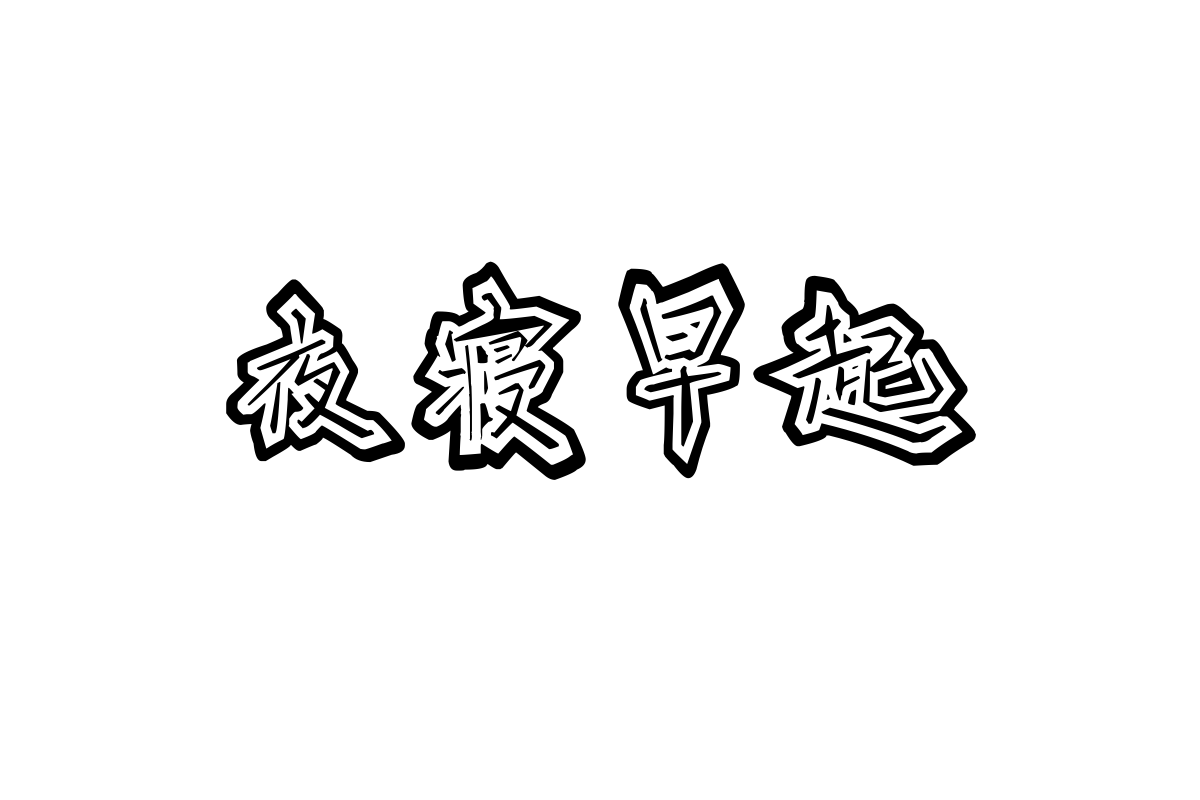
汉仪新蒂涂鸦体是一种现代的中文字体,具有独特的艺术风格和设计特点。这种字体的特点是笔画流畅、线条粗犷,给人一种强烈的视觉冲击力。它的笔画粗细不一,既有尖锐的棱角,又有柔和的弧度,使得整体视觉效果更加丰富多变。此外,汉仪新蒂涂鸦体的字形结构也独具匠心,每个字都有其独特的形态和结构,使得整款字体充满了个性和艺术感。
总的来说,汉仪新蒂涂鸦体是一种非常独特且富有创意的中文字体,它不仅能够很好地表达出现代年轻人的审美观念,也能够为各种设计作品增添一份独特的魅力。